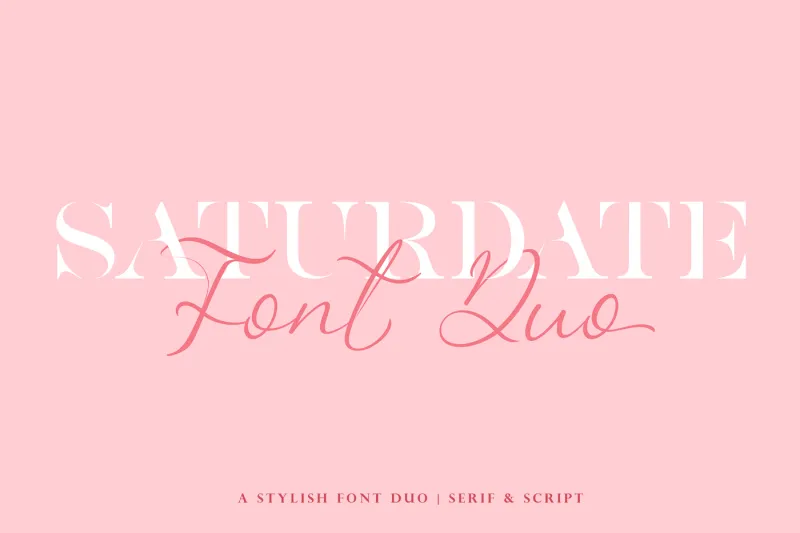
Saturdate Font Duo – Fonte Grátis
Saturdate Font Duo
A Saturdate Font Duo é uma elegante dupla de fontes com estilo serif e script, perfeitamente projetada para agregar sofisticação a qualquer design. Esta fonte vem integrada com um ‘signature’ e uma versão em letra maiúscula bold e serifada. A proposta de uso desta dupla é simples e elegante, tornando-a ideal para várias aplicações gráficas como logotipos de marca, selinhos digitais, capas de álbum, cartões de visita, citações e muito mais. Ideal para designers que valorizam uma apresentação sofisticada, a Saturdate é fácil de usar e oferece um ótimo nível de leitura. Ela traz um toque distinto sem deixar de ser versátil e eficaz em diversos ambientes gráficos, tornando-a uma opção perfeita para quem busca estilo e facilidade ao criar suas projetos visuais.